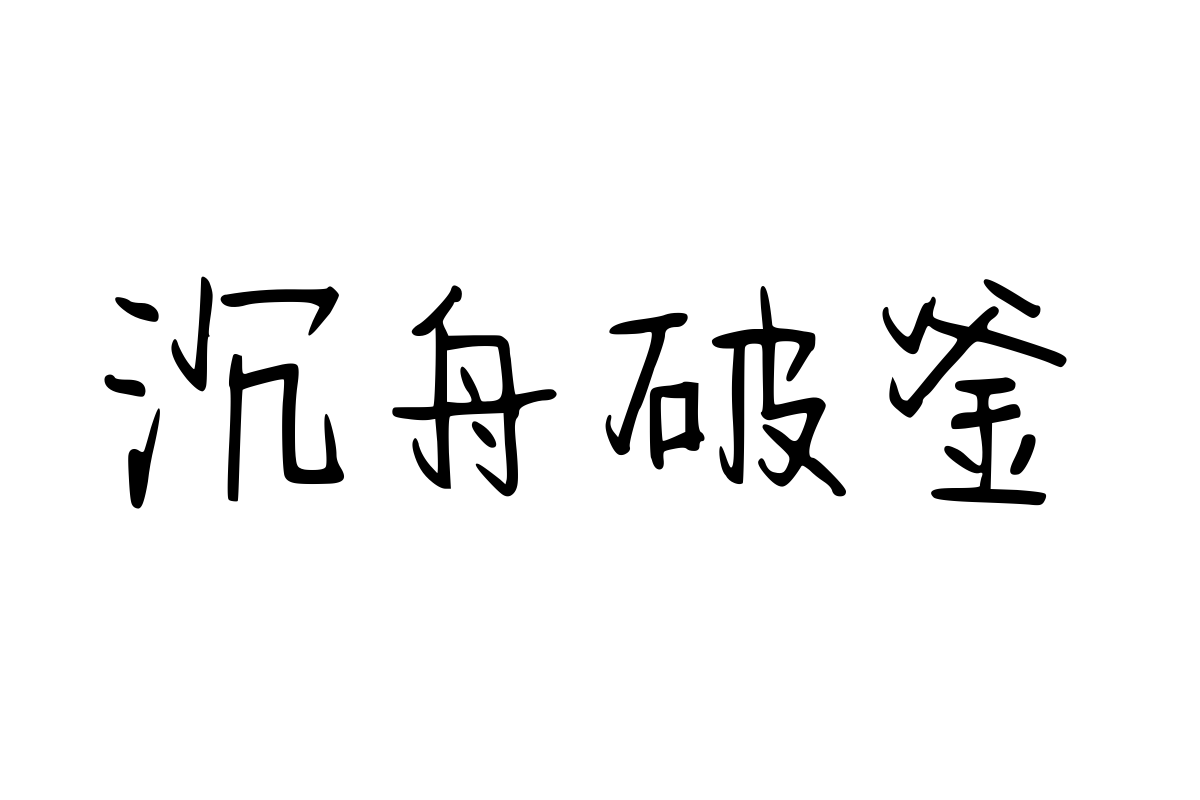
思雨静守从容是一款具有现代感的中文字体,适用于各种商业、办公、广告等领域。该字体的特点是线条流畅,字形优美,给人一种宁静、舒适的感觉。
思雨静守从容的笔画粗细适中,线条流畅有力,既符合现代人的审美需求,又不失传统书法的韵味。其字形结构严谨,笔画转折自然,给人一种沉稳、大气的感觉。
该字体适用于标题、正文、广告等需要展示个性和品味的场合。无论是用于书籍、杂志、报纸还是网页设计,都能展现出独特的艺术魅力。